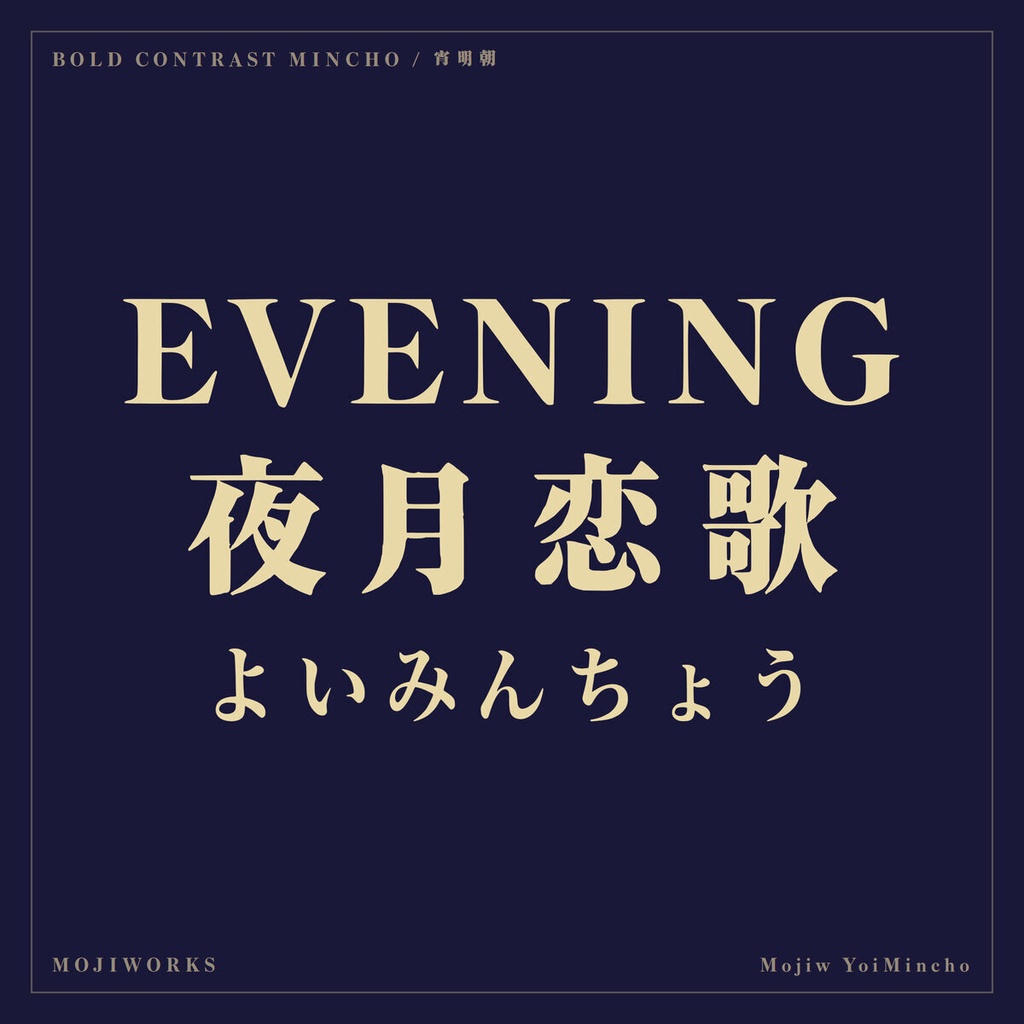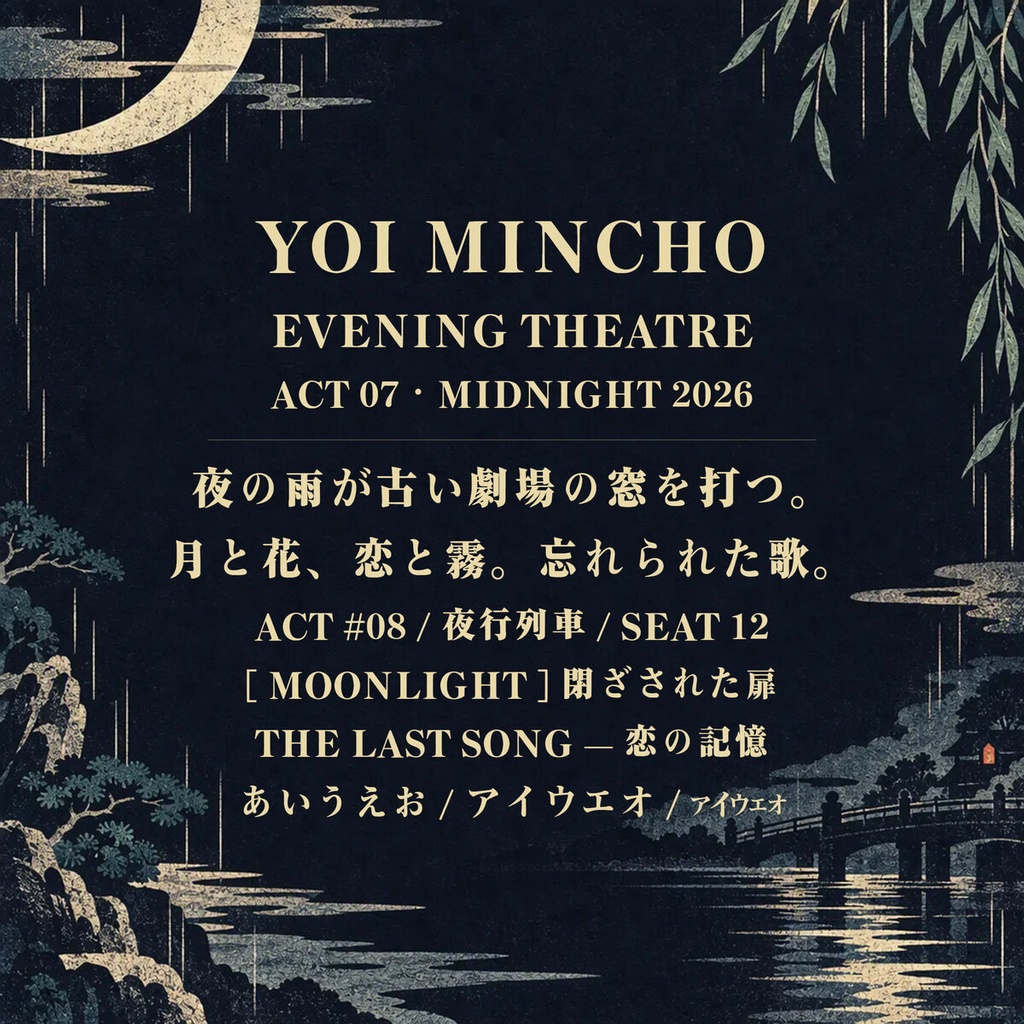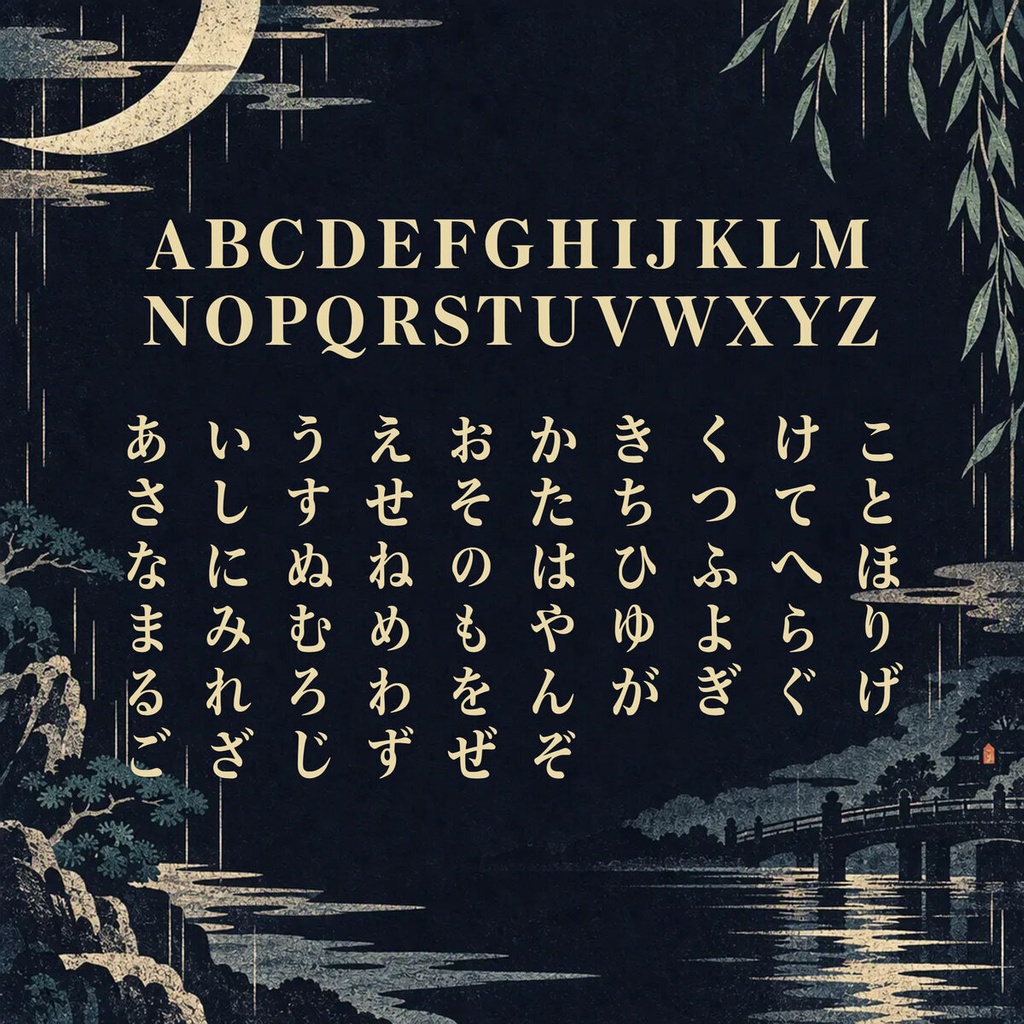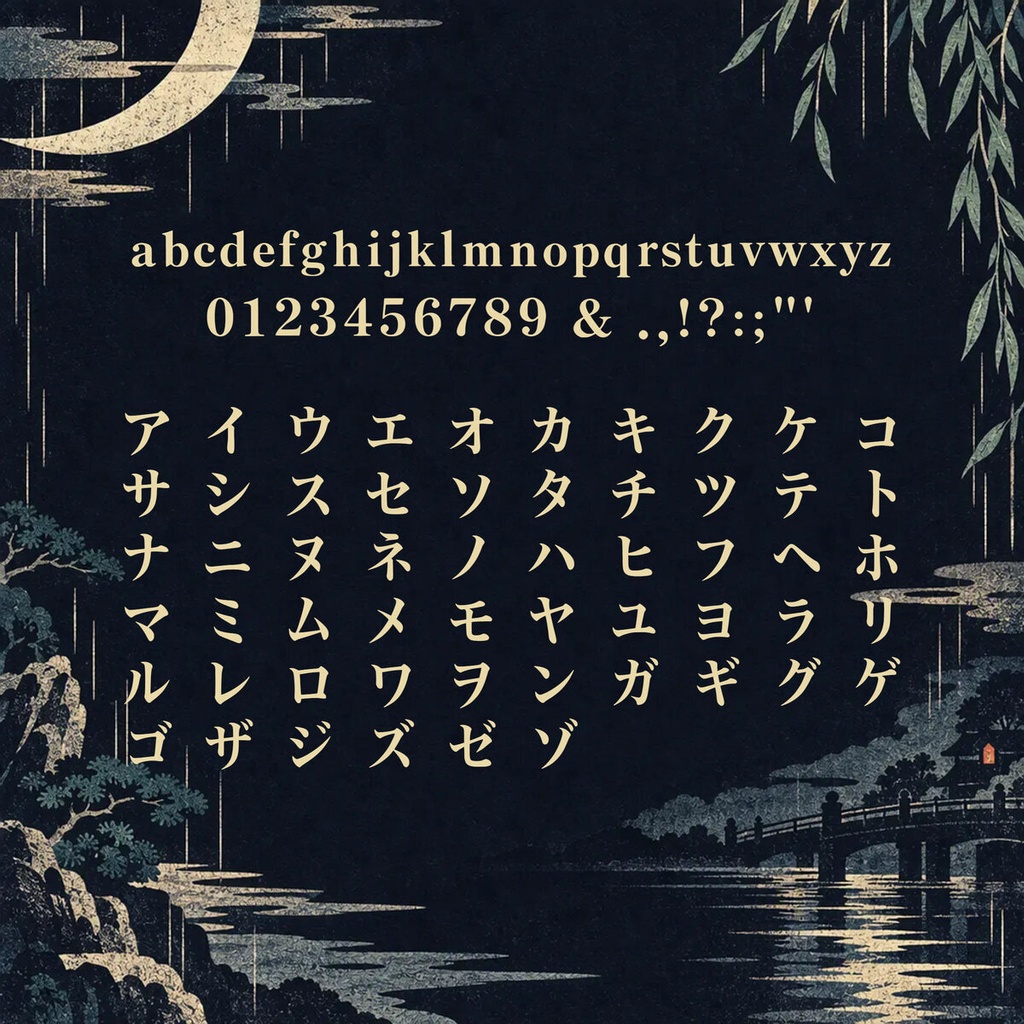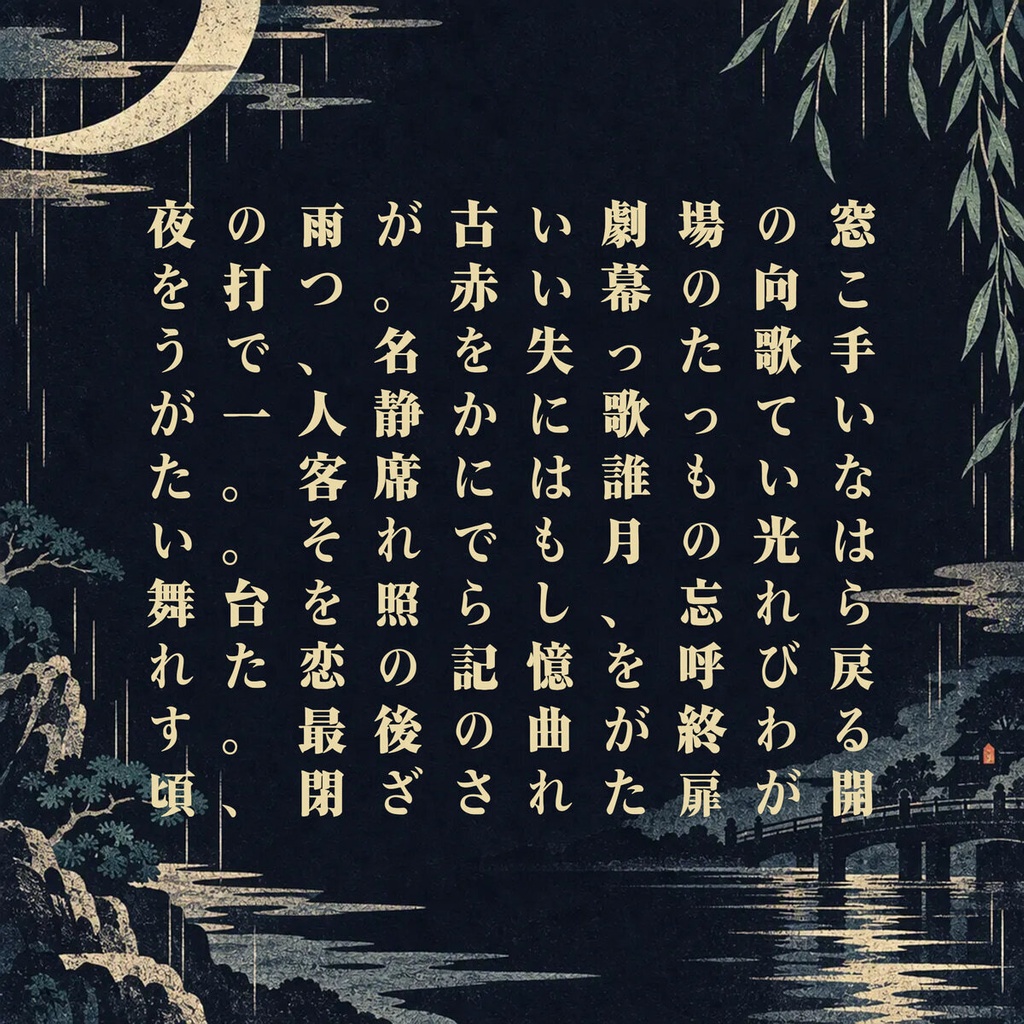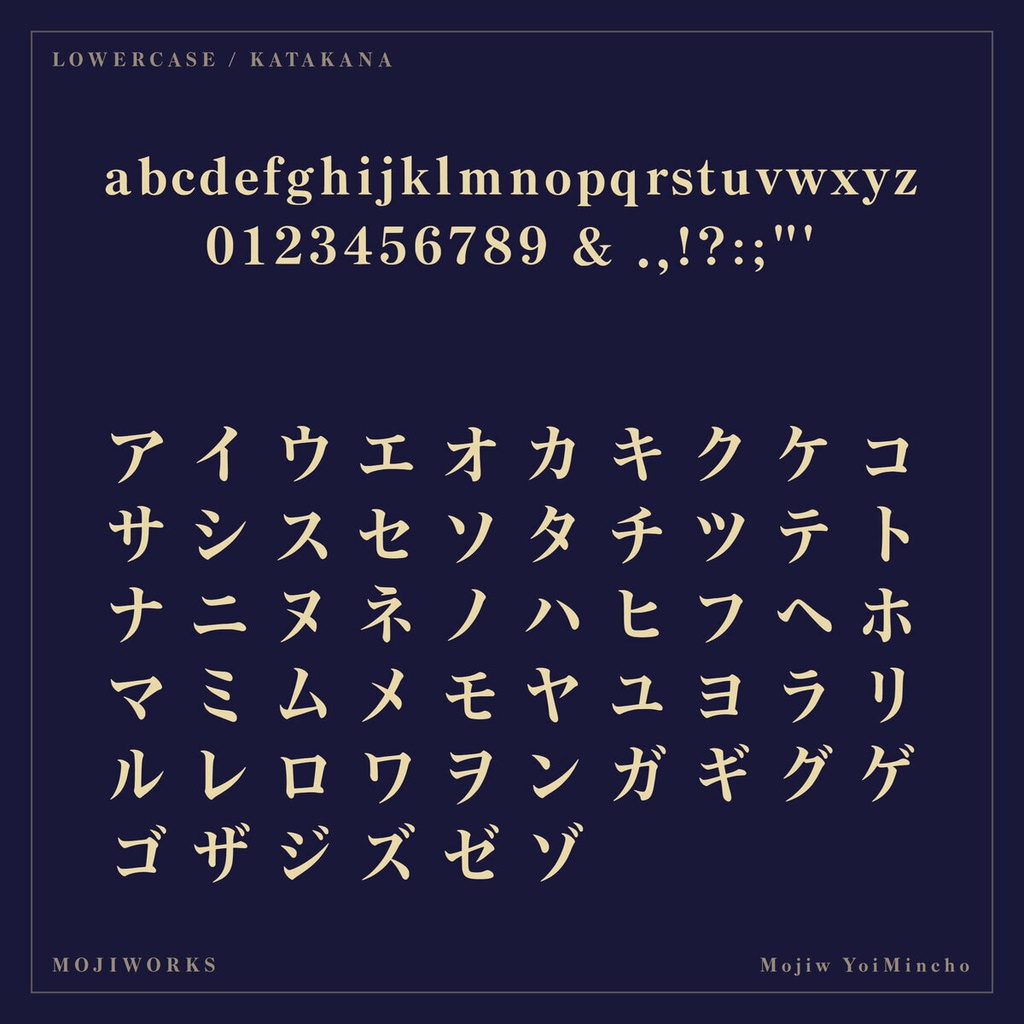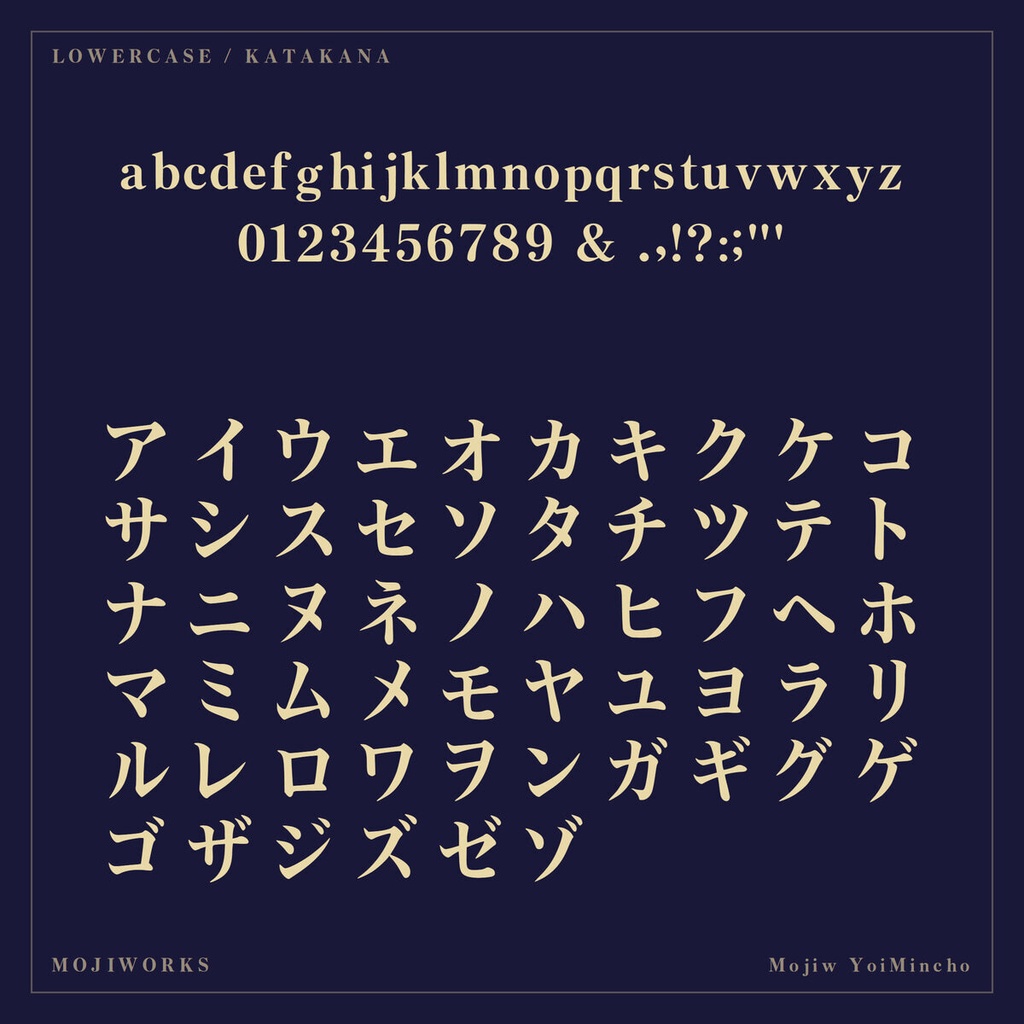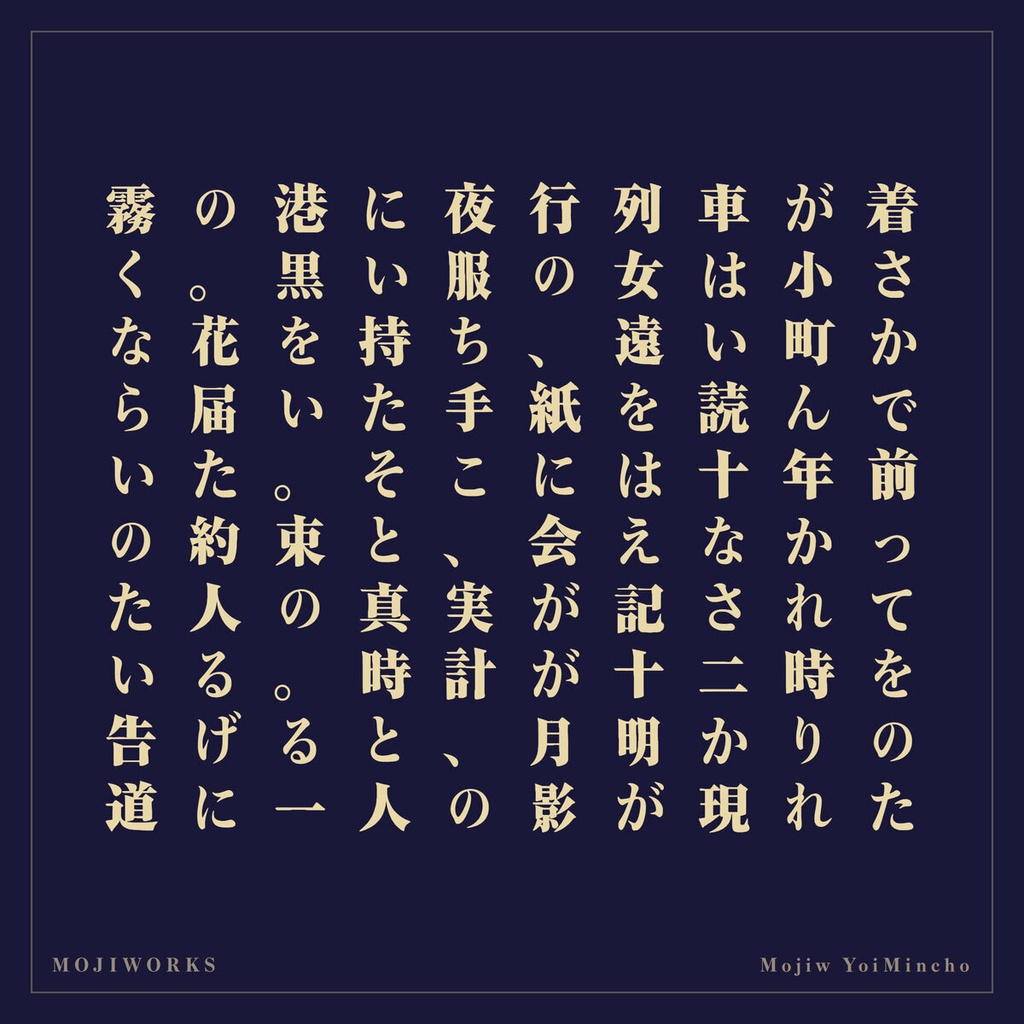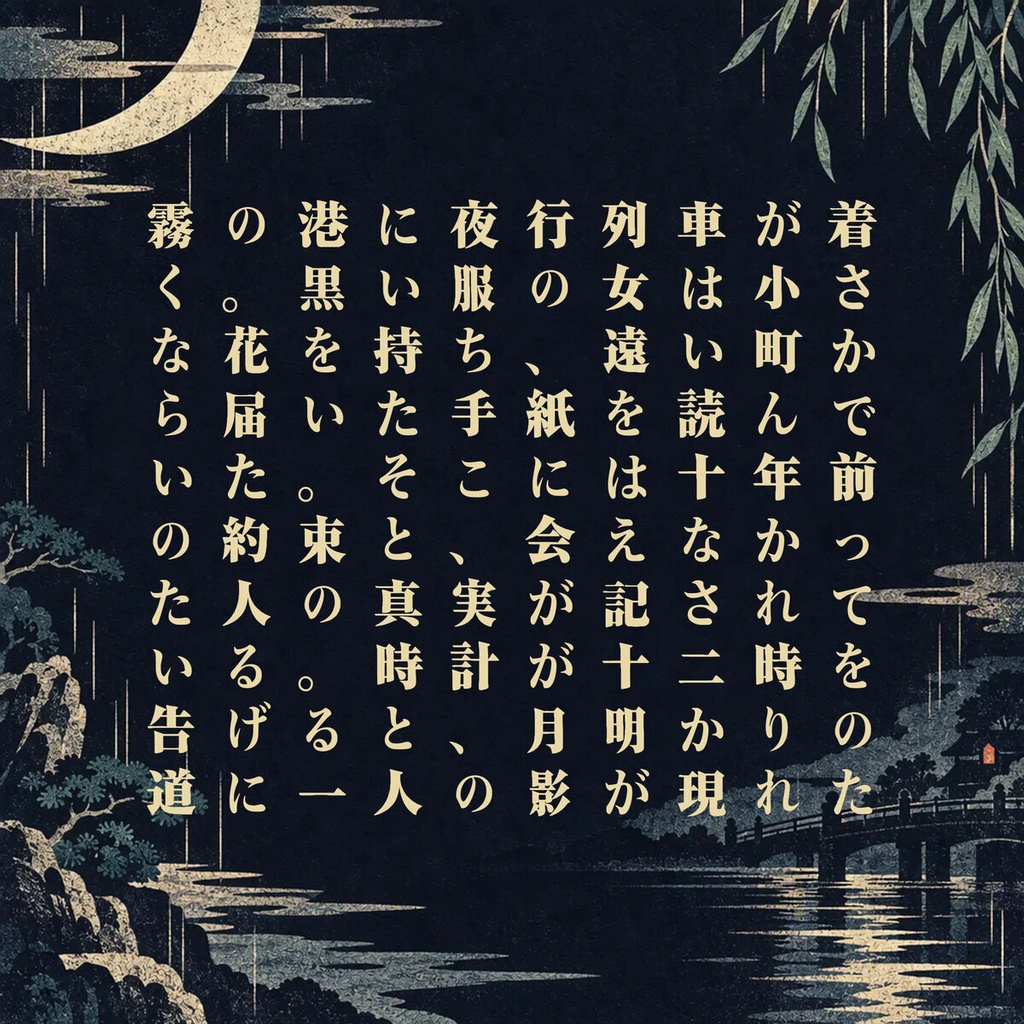
宵明朝 YoiMincho【フォント】 — 夜に映えるエモーショナル明朝|常用漢字2,136字
夜のしずけさと刃のようなコントラストをまとった、エモーショナルな明朝体です。 An emotional high-contrast Mincho with the stillness and sharp edge of night. 【用途 / Use】 歌詞MV / 詩集 / 同人小説タイトル / アルバムジャケット For lyric videos, poetry, novel titles, and album artwork. 【常用漢字フル版 / Joyo Complete】 常用漢字2,136字を完全収録し、ラテン文字・ひらがな・カタカナ・記号を含む全2,437文字を収録しています。半角カナは収録していません。 Includes all 2,136 Joyo kanji and 2,437 characters total, including Latin, hiragana, katakana, and punctuation. Half-width kana are not included. 2437文字 / characters 【関連する収録版 / Other Edition】 ラテン文字・かな・記号を収録したスタンダード版もあります。 The Standard edition includes Latin, kana, and punctuation. ▶ スタンダード版 / Standard: https://mojiworks.booth.pm/items/8826762 【フォント仕様 / Specification】 バージョン / Version: 1.0.1 形式 / Format: TrueType (.ttf), Web (.woff2) 対応環境 / Platform: Windows, macOS, web browsers 収録字一覧 / Character list: CHARSET.txt 同梱 / Included: font files, README, LICENSE, character list, portfolio PDF, product previews. 【利用規約 / License Summary】 個人・商用利用可。1ライセンスは購入者1名に適用されます。 Personal and commercial use is permitted. One license covers one purchaser. 印刷・動画・ロゴ・グッズ等の静的成果物、および購入者が運営するサイトでの同梱WOFF2の利用が可能です。 Static output such as print, video, logos, and merchandise is permitted. The bundled WOFF2 may be used on a website owned or operated by the purchaser. ゲーム・アプリへの組み込みは、利用者が生のフォントを抽出できない形式に限ります。生のフォントを同梱する場合は別途ライセンスをご相談ください。 Game/app embedding requires protection against extraction of the raw font. Contact us for a separate runtime-embedding license when shipping raw font files. 標準ライセンスは1製品・1サイトあたり年間約100,000ユーザーまで。従業員50名超の組織を含む大規模利用は要相談。 Standard coverage is approximately 100,000 users per product/site/year. Larger use and organizations with more than 50 employees require an extended license. フォント本体の再配布・販売・貸与・変換・グリフ抽出・派生フォント制作・生成AI学習やスタイル参照は禁止です。 Redistribution, resale, lending, conversion, glyph extraction, derivative fonts, and generative-AI training or style reference are prohibited. 完全な利用条件は同梱の LICENSE.txt / LICENSE.jp.txt をご確認ください。 The bundled license files are authoritative; consult them for the complete terms. 【ほかのフォント・カスタム制作 / More Fonts and Custom Work】 フォント一覧、オーダーメイド書体、文字追加、拡張ライセンスのご相談はこちら。 Browse our catalog or contact us for custom typefaces, added characters, and extended licenses. https://mojiworks.booth.pm/